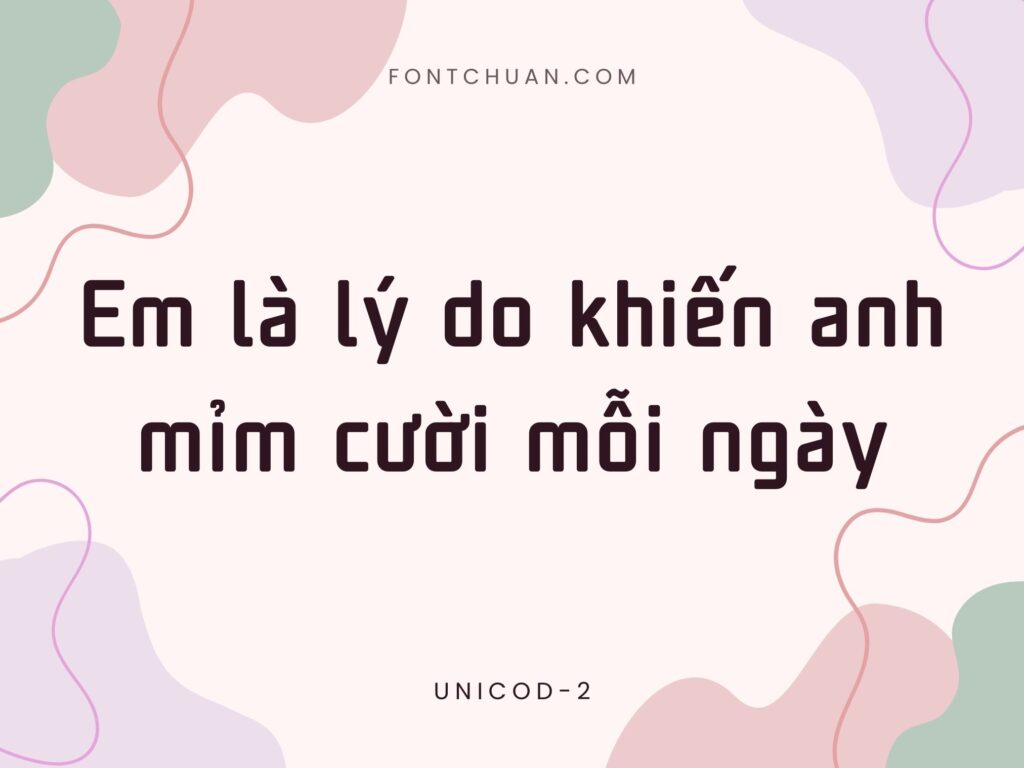
Font Unicod Việt Hóa
Unicod.otf là một font chữ Unicode, cho phép hiển thị một phạm vi rộng các ký tự từ nhiều ngôn ngữ và hệ thống viết khác nhau. Font Unicode được thiết kế để hỗ trợ hầu hết các ký tự được định nghĩa trong tiêu chuẩn Unicode, giúp đảm bảo tính tương thích và hiển thị chính xác trên nhiều nền tảng và ứng dụng. Với khả năng hiển thị các ký tự một cách đều đặn và rõ ràng, Unicod.otf còn mang đặc điểm tương tự như Font Monospace, rất hữu ích trong các tài liệu kỹ thuật hoặc lập trình. Font này hỗ trợ đầy đủ tiếng Việt và nhiều ngôn ngữ khác, được sưu tầm và đăng bởi thành viên của Font Chuẩn.
Font có thiết kế đơn giản và rõ ràng, phù hợp cho các tài liệu văn bản, trang web và ứng dụng yêu cầu hỗ trợ đa ngôn ngữ. Các ngành nghề như giáo dục, công nghệ, quảng cáo và bất động sản có thể tận dụng hiệu quả font này. Ngoài ra, Unicod.otf cũng thích hợp cho các sự kiện như lễ hội, sinh nhật, ngày Nhà giáo, Valentine, và có thể sử dụng như một Font chữ Giáng Sinh để trang trí thiệp, poster hay banner mùa lễ hội, mang đến không khí rộn ràng, vui tươi cho các sản phẩm thiết kế.